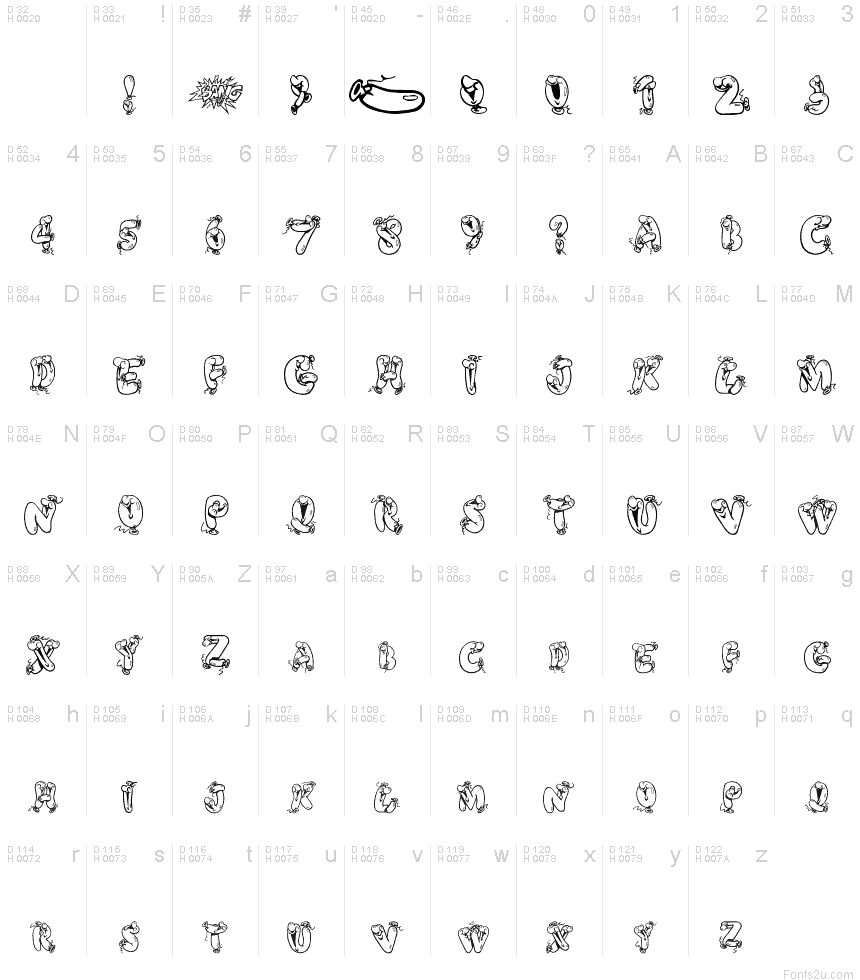
Helium Heaven di Beeline è un carattere display cartoon gratuito che sembra una fila di animaletti di palloncini pronti a comporre il tuo messaggio. Ogni lettera appare gonfia d'aria e traballante sui suoi contorni spessi, con piccoli nodi e curve che le danno quell'aspetto di decorazione appena fatta a una festa. C'è un'energia spontanea, disegnata a mano, che rende il tutto leggero, simpatico e immediatamente accogliente.
Usando Helium Heaven, il tuo testo sembra quasi fluttuare fuori dalla pagina: è la scelta perfetta per inviti di compleanno, striscioni per feste, confezioni di giocattoli, poster scolastici, volantini di carnevale e grafiche giocose per i social media. Questo font gratuito dà il meglio di sé nei grandi formati, dove le sue espressioni buffe possono risaltare; abbinalo a un carattere sans serif semplice e arrotondato per il testo principale, in modo che queste lettere spumeggianti rimangano le vere protagoniste.